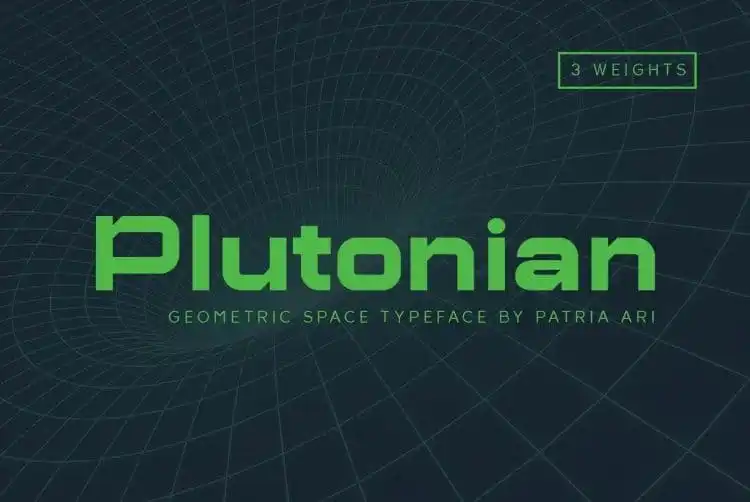
A Plutonian Display Font é uma fonte moderna e robusta sem serif que inspirou-se no tema aeronáutico espacial. Sua tipografia é cuidadosamente kernada para dar uma impressão sólida e forte, ideal para criar elementos visuais impactantes em designs variados. Esta fonte vem em três diferentes pesos e foi feita usando formas geométricas simplificadas, tornando-a versátil para um leque ampla de aplicabilidades. Seja ela usada no logotipo de sua marca ou em seu próximo projeto editorial, a Plutonian Display Font oferece uma combinação perfeita de simplicidade e força que certamente chamará atenção. Com esta fonte poderosa, você terá as ferramentas para criar um design impactante, adequada tanto para o desenvolvimento de PowerPoint como para criações publicitárias em grande escala ou até mesmo sinalização urbana.